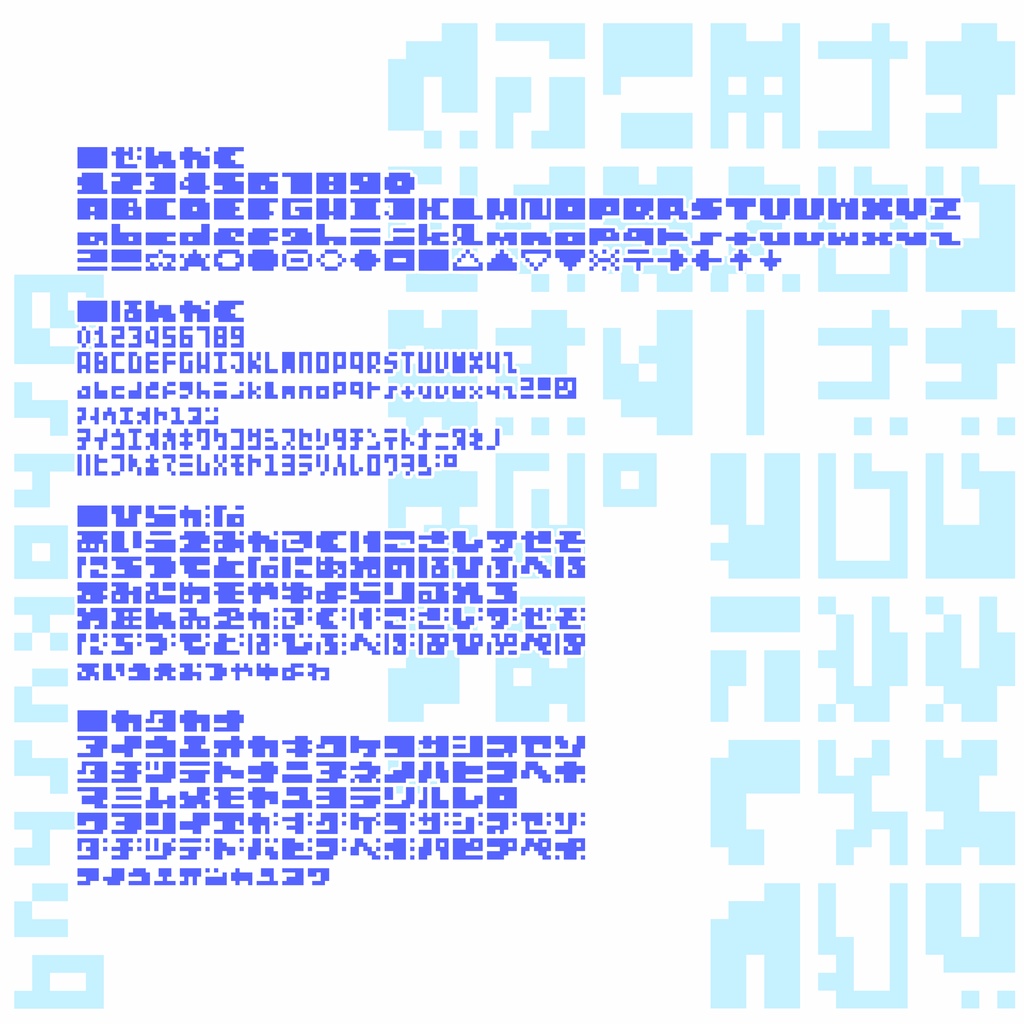
フリーフォント「カクガクネメブ」(無料・商用可)【不定期配布】
多忙のため事前に開けておきます。(〜R8.4.10まで配布予定) ______________________________ 毎年4/10&気が向いたとき&イベント時に配布予定のフォントです。 ______________________________ 「カクガクネメブ(Qma-kakugakunemeb.ttf)」は フォント作成について何も知らない触手(加熱九真/shokushuQ)が https://www.pentacom.jp/pentacom/bitfontmaker2/ さんの力によって、手打ちしてつくったドットのフォントです。 何も知らないので横書きのことしか考えていません。 なお、カクガクネメブはカクガクネメス( https://nekkiq.booth.pm/items/5644284 )をベースにしています。 ■利用範囲 個人利用、商用利用、ウェブフォントやゲームなど独自性のあるコンテンツへの組み込みは自由です。 年齢制限が必要なコンテンツにもご使用頂けます。 ■禁止事項 犯罪行為や違法行為への使用、改変前のフォントファイルを単独で再配布することは禁止します。 商標登録など、第三者が本フォントを使用できなくなる行為は禁止します。 ■改変と再配布 収録文字の8割以上を改変し、本規約を改変前フォントの規約として明記・同梱することで再配布可能です。 ■免責 本フォントの使用により生じた損害について、制作者(加熱九真/shokushuQ)は一切の責任を負いません。 ■その他 必須ではありませんが、使用の際にクレジット記載があると嬉しいです。 ■収録文字について 全角スペースはかなり中途半端な幅です(修正方法模索中) 半角スペースを1ピクセル分にしてあるので、それでうまく調整してください。 ■全角 1234567890 ABCDEFGHIJKLMNOPQRSTUVWXYZ abcdefghijklmnopqrstuvwxyz ?!☆★○●◎◇◆□■△▲▽▼※〒→←↑↓ ■半角 0123456789 ABCDEFGHIJKLMNOPQRSTUVWXYZ abcdefghijklmnopqrstuvwxyz?!@ ァィゥェォャュョッ アイウエオカキクケコサシスセソタチツテトナニヌネノ ハヒフヘホマミムメモヤユヨラリルレロワヲン゙゚ ■ひらがな あいうえお かきくけこ さしすせそ たちつてと なにぬねの はひふへほ まみむめも やゆよ らりるれろ わをんゐゑ がぎぐげご ざじずぜぞ だぢづでど ばびぶべぼ ぱぴぷぺぽ ぁぃぅぇぉ っゃゅょゎ ■カタカナ アイウエオ カキクケコ サシスセソ タチツテト ナニヌネノ ハヒフヘホ マミムメモ ヤユヨ ラリルレロ ワヲンイヱ ガギグゲゴ ザジズゼゾ ダヂヅデド バビブベボ パピプペポ ァィゥェォ ッャュョヮ